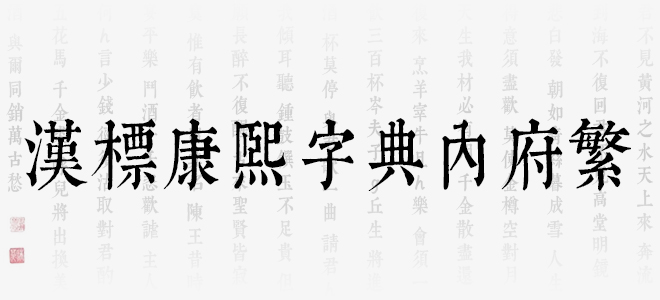
漢標(biāo)康熙字典內(nèi)府繁字體是以康熙字典為藍本運用軟件制作而成,筆畫流暢飛揚繁簡結(jié)合,結(jié)體左緊右松,開合對比強烈,進一步強化了動感。整套字體有如一氣呵成,行筆迅捷華麗,其個性浪漫灑脫,適用于現(xiàn)代詩歌、短文的排版,以及文化、商業(yè)類品牌的廣告語設(shè)計。歡迎喜歡漢標(biāo)康熙字典內(nèi)府繁字體的朋友前來下載使用。
漢標(biāo)康熙字典內(nèi)府繁